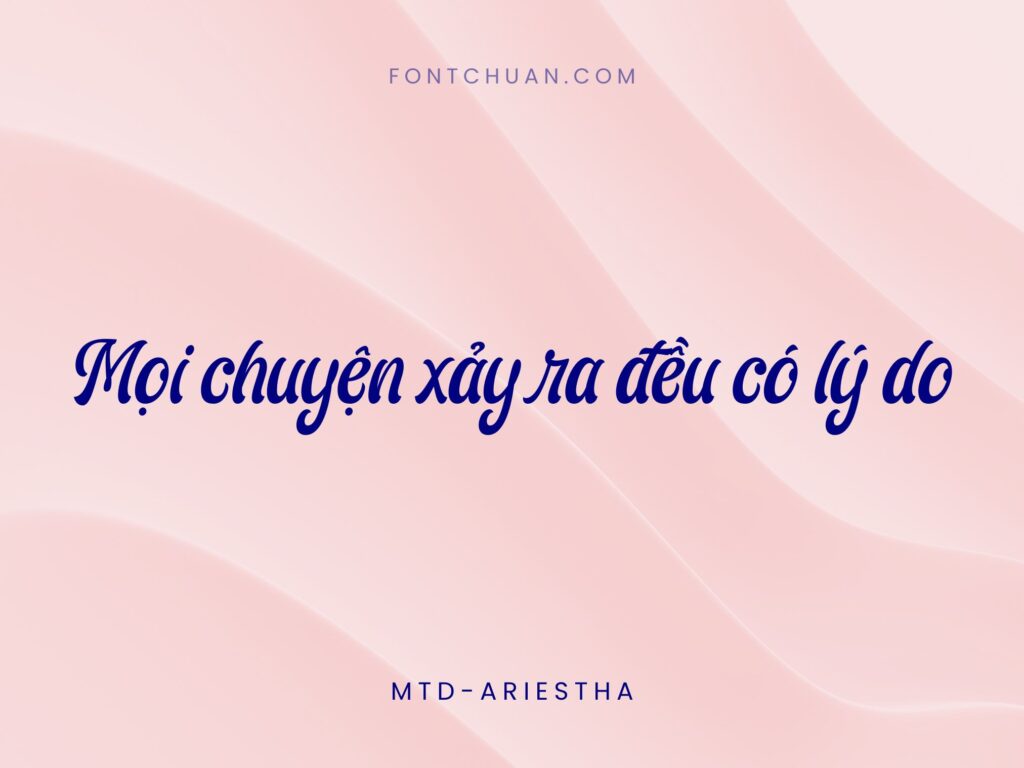
Font Ariestha Script là một kiểu chữ viết tay mang phong cách cổ điển, được thiết kế bởi Arterfak Project. Với các nét chữ uyển chuyển và tinh tế, Ariestha Script mang lại sự thanh lịch và nghệ thuật cho các thiết kế, phù hợp cho nhiều dự án sáng tạo.
Phiên bản Ariestha Script đã được Việt hóa bởi Mộc Hạ, hỗ trợ đầy đủ tiếng Việt cùng hơn 64 ngôn ngữ khác như Anh, Pháp, Tây Ban Nha, Đức, Ý và Bồ Đào Nha, mở rộng khả năng ứng dụng trong thiết kế đa ngôn ngữ. Font này đã được thành viên Font Chuẩn sưu tầm và chia sẻ, đáp ứng nhu cầu của cộng đồng thiết kế. Với thiết kế bao gồm các ký tự viết tay mềm mại và ligatures độc đáo, Ariestha Script phù hợp cho các ứng dụng như thiết kế logo, thiệp mời, bao bì sản phẩm và các ấn phẩm quảng cáo. Các ngành nghề như quảng cáo, giáo dục, công nghệ và ẩm thực có thể tận dụng font này để tạo ra thiết kế ấn tượng và thu hút.